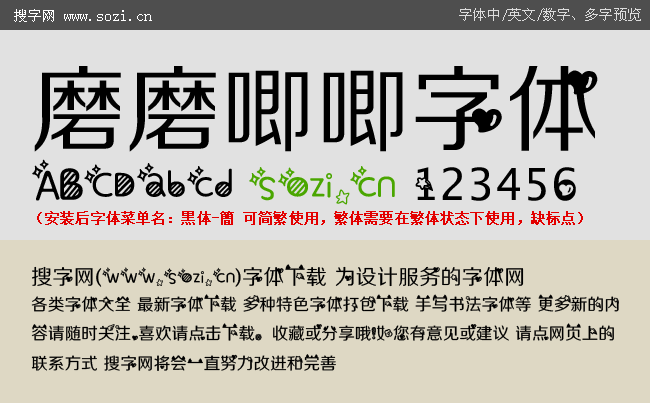
磨磨唧唧字體
搜字網(wǎng)提供一款磨磨唧唧字體手機(jī)中文字體下載,磨磨唧唧字體是以正準(zhǔn)黑簡(jiǎn)體為原形,在字體間嵌入了一些可愛(ài)的卡通圖形,正準(zhǔn)黑端正簡(jiǎn)潔,藝術(shù)性強(qiáng),加入卡通圖案后又帶有趣味性,喜歡的朋友快快下載吧。